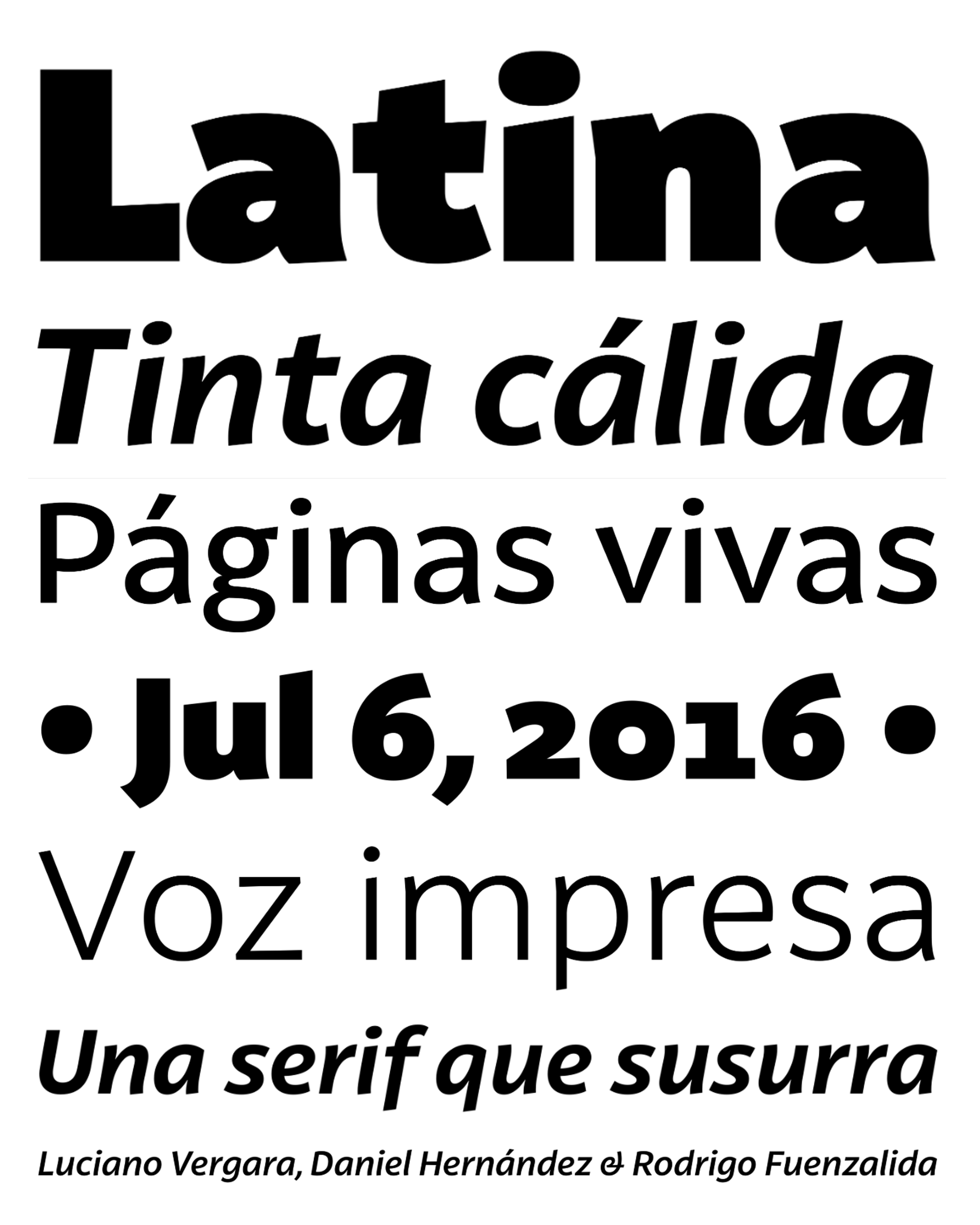
| Año | 2016 |
| Créditos | Luciano Vergara, Daniel Hernández, Rodrigo Fuenzalida, Latinotype Team |
| Descripción | Latina es nuestro primer tipo de letra humanista diseñado para su uso en texto continuo. Este tipo de letra se basa en la caligrafía, pero los rasgos caligráficos se han modificado para hacer de Latina un tipo de letra más neutro. Así se evita que los lectores pierdan la concentración al leer texto continuo. Por otro lado, estos mismos rasgos se resaltan cuando se utiliza el tipo para titulares o texto de presentación. Esta familia de 11 pesos incluye cursiva y versalitas, y admite 219 idiomas diferentes, así como varios juegos de cifras. Latina es la elección perfecta para el diseño editorial (libros y revistas), la creación de marcas y la publicidad. |
| Familia(s) | Thin, Thin Italic, Ultra Light, Ultra Light Italic, Light, Light Italic, Regular, Regular Italic, Semi Bold Italic, Medium, Medium Italic, Bold, Bold Italic, Ultra Bold, Ultra Bold Italic, Black, Black Italic, Heavy, Heavy Italic, Ultra Heavy, Ultra Heavy Italic |
| Estilos | 22 |